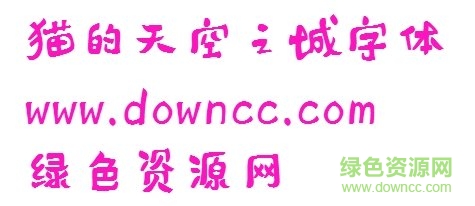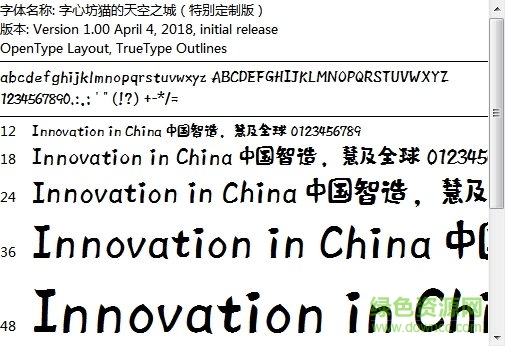
貓的天空之城字體是出自字心坊字庫的一款時(shí)尚可愛的卡通字體,風(fēng)格清秀大方,字跡粗獷而淡雅,給人十分出彩的設(shè)計(jì)體驗(yàn),喜歡的朋友就來綠色資源網(wǎng)試試吧!
該字體由字心坊為貓的天空之城特殊定制。字心坊基于貓的天空之城LOGO的設(shè)計(jì)風(fēng)格,運(yùn)用貓空的設(shè)計(jì)元素逐一設(shè)計(jì)出符合國(guó)家GB2312-80字符集標(biāo)準(zhǔn)的6763個(gè)字形,最后編譯出整套字庫。字體風(fēng)格文藝、新穎、可愛、卡通、小清新。